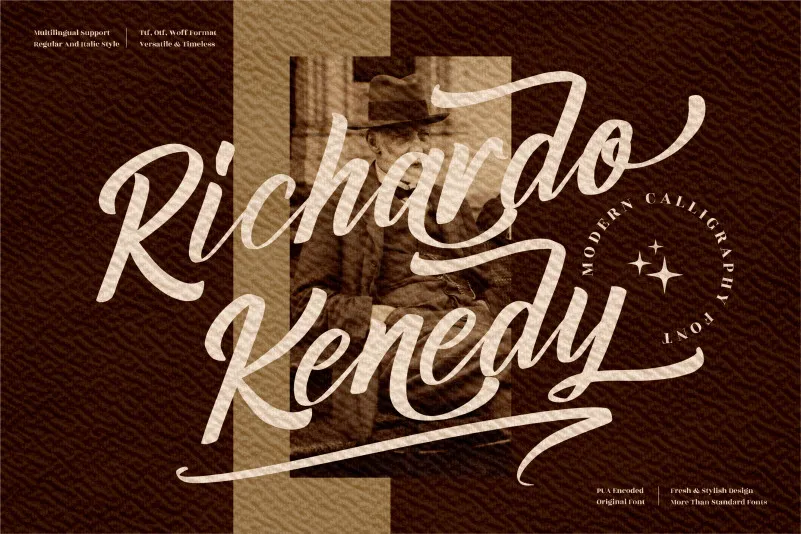
Richardo Kenedy Font – Download Grátis
A Richardo Kenedy Font é uma excelente opção para projetos que exigem um toque de elegância e sofisticação, seja para criações digitais ou impressas. Inspirada no estilo da grafia livre, esta fonte premium é perfeita para qualquer tipo de projeto, desde logos e identidades visuais até produtos personalizados como mugs e etiquetas. Suas linhas finas e agradáveis ao olhar combinam harmoniosamente com diferentes formatos de texto, tornando-a ideal para designs variados como cartões de nome, convites, cupons de desconto e capas de livros. Com Richardo Kenedy Font, você pode garantir um toque especial em seus projetos que valorizam o luxo, seja em uma loja local ou no seu site online.